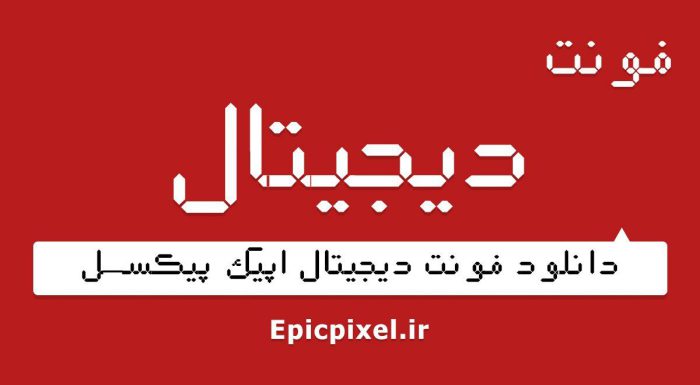
11 فونت دیجیتال فارسی
دنیای دیجیتال خود را با فونتهای طرح دیجیتال فارسی متحول کنید
فونتها، ستونهای زیبای دنیای دیجیتال، نقش بهسزایی در انتقال پیام و برقراری ارتباط بصری مؤثر دارند. در دنیای طراحی گرافیک فارسی، فونتهای طرح دیجیتال حرفی تازه میزنند. این فونتها با الهام از دنیای دیجیتال، ظاهری مدرن و چشمنواز دارند و میتوانند جلوهای خاص به پروژههای شما ببخشند.
در این مقاله، با دنیای فونتهای طرح دیجیتال فارسی آشنا میشویم. ویژگیهای این فونتها را بررسی میکنیم و به شما میگوییم که از کجا میتوانید آنها را دانلود کنید. پس با ما همراه باشید.
فونت طرح دیجیتال فارسی چیست؟
فونت طرح دیجیتال فارسی، نوعی فونت است که با الهام از سبکهای دیجیتال و فونتهای کامپیوتری طراحی میشود. این فونتها معمولا دارای خطوط صاف، گوشههای تیز و ظاهری مینیمالیستی هستند.
دانلودفونتهای طرح دیجیتال فارسی حس مدرنیته و پیشرفت را القا میکنند و برای استفاده در پروژههای مختلفی مانند:
- طراحی وبسایت و اپلیکیشن
- طراحی پوستر و بنرهای تبلیغاتی
- طراحی لوگو و هویت برند
- ساخت محتوا در شبکههای اجتماعی
- اسلایدهای پاورپوینت و ارائههای تجاری
مناسب هستند.
ویژگیهای فونت طرح دیجیتال فارسی
فونتهای طرح دیجیتال فارسی علاوه بر ظاهر مدرن و چشمنواز، دارای ویژگیهای دیگری نیز هستند که آنها را برای طراحان گرافیک فارسی جذاب میکند. برخی از این ویژگیها عبارتند از:
- خوانایی بالا: بسیاری از فونتهای طرح دیجیتال بهگونهای طراحی شدهاند که خوانایی خوبی دارند و حتی در سایزهای کوچک نیز بهراحتی قابل خواندن هستند.
- قابل انعطاف بودن: این فونتها را میتوان با وزنهای مختلف (Light, Regular, Bold) و همچنین بهصورت ایتالیک استفاده کرد. این انعطافپذیری به شما امکان میدهد تا در پروژههای خود تنوع ایجاد کنید.
نکاتی برای استفاده از فونتهای طرح دیجیتال فارسی
- استفاده به اندازه: از فونتهای طرح دیجیتال بهصورت متعادل استفاده کنید. استفاده بیش از حد از این فونتها میتواند باعث شلوغی و آشفتگی در طراحی شما شود.
- ترکیب با فونتهای دیگر: گاهی اوقات میتوانید فونتهای طرح دیجیتال را با فونتهای دیگر مانند فونتهای Serif یا Script ترکیب کنید تا به تعادل و تنوع در طراحی خود برسید.
- آزمایش و خلاقیت: از خلاقیت خود استفاده کنید و فونتهای مختلف را امتحان کنید تا به بهترین نتیجه برای پروژه خود برسید.
نمونههایی از فونتهای طرح دیجیتال فارسی محبوب
- فونت ایران سنس: این فونت یکی از محبوبترین فونتهای طرح دیجیتال فارسی است که دارای ظاهری مدرن و خوانایی بالا است.
- فونت وزیر: این فونت نیز از جمله فونتهای پرکاربرد در طراحیهای دیجیتال است که ظاهری مینیمالیستی و هندسی دارد.
- فونت صبا: این فونت با الهام از خط نستعلیق طراحی شده است و برای استفاده در پروژههایی که نیاز به ظاهری سنتیتر دارند مناسب است.
- فونت یکان: این فونت دارای تنوع وزنی و ایتالیک است و برای استفاده در عناوین و متنهای مختلف مناسب است.
5 سوال متداول درباره فونتهای طرح دیجیتال فارسی
1. فونتهای طرح دیجیتال فارسی چه مزایایی دارند؟
فونتهای طرح دیجیتال فارسی دارای مزایای متعددی هستند از جمله:
- ظاهر مدرن و چشمنواز
- خوانایی بالا
- انعطافپذیری و تنوع
- سازگاری با نرمافزارهای گرافیکی
2. از فونتهای طرح دیجیتال فارسی در چه پروژههایی میتوان استفاده کرد؟
از فونتهای طرح دیجیتال فارسی میتوان در پروژههای مختلفی مانند طراحی وبسایت، اپلیکیشن، پوستر، بنر، لوگو، هویت برند، محتوا در شبکههای اجتماعی، اسلایدهای پاورپوینت و ارائههای تجاری استفاده کرد.
5. چند نمونه از فونتهای طرح دیجیتال فارسی محبوب کدامند؟
فونتهای طرح دیجیتال فارسی دنیای جدیدی از امکانات را به روی طراحان گرافیک فارسی گشودهاند. با استفاده از این فونتها میتوانید به پروژههای خود ظاهری مدرن و چشمنواز ببخشید و پیام خود را بهطور مؤثرتر به مخاطبان خود منتقل کنید.